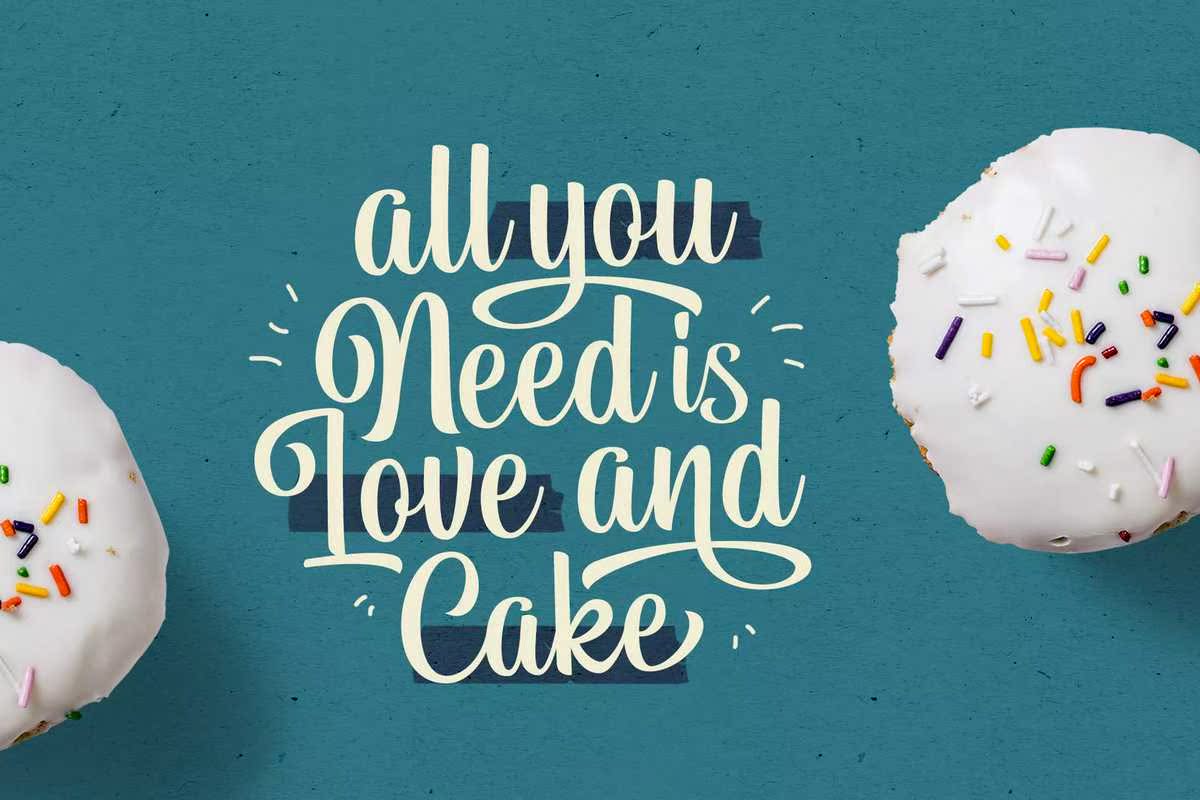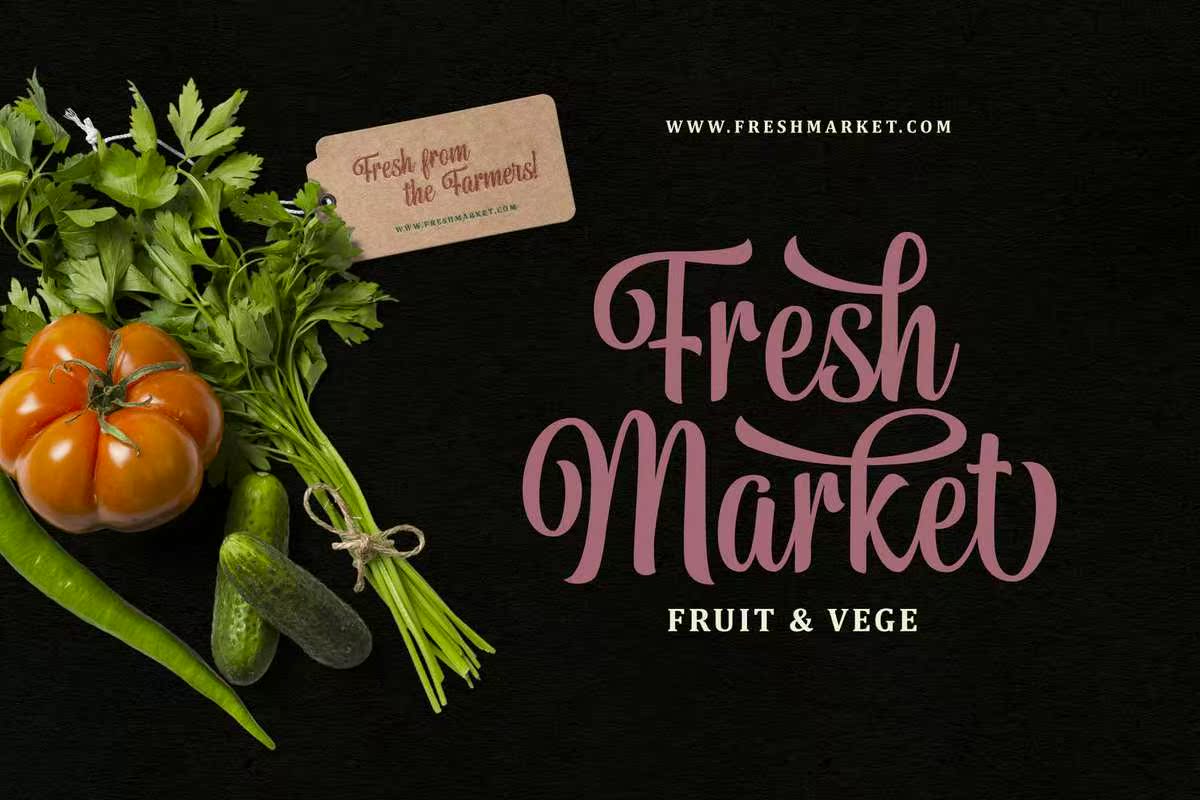
BelymonScript是一款独一无二的经典剧本,一眼就能看懂。非常适合需要字体的用户,特别是在标识、服装、邀请、品牌、包装、广告等方面。此剧本列表集的主要功能是为每个角色设置6套以上的角色!只要随便玩,你就会喜欢它。这种字体包括大写、小写、标点符号、符号和数字、文体设置交替、连字等,支持多种语言和语音编码。BelymonScript是一种经典的、一目了然的脚本。非常适合需要字体的人,特别是在标识、服装、邀请、品牌等方面,包装、广告等。本脚本的主要功能为:列表设置每个角色支持6集!只要随便玩,你会喜欢的。这种字体包括大写、小写、标点符号、符号和数字、文体设置交替、连字等,因此支持多语言和alreadypuaencoded。